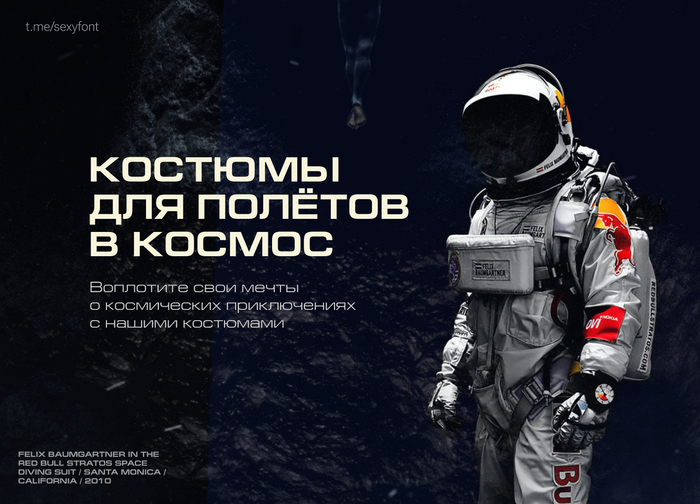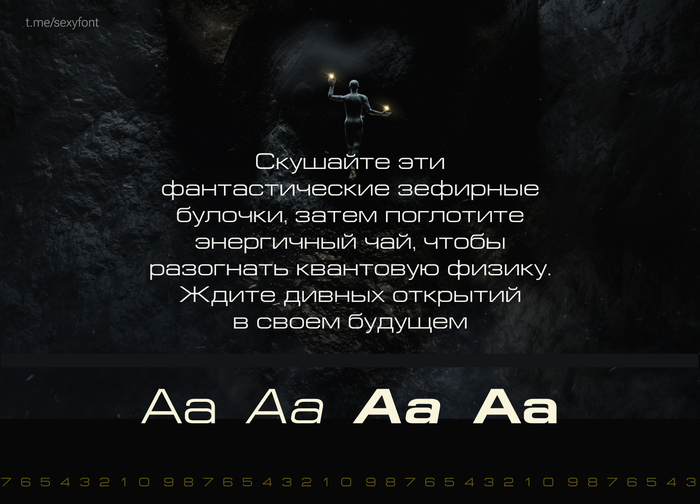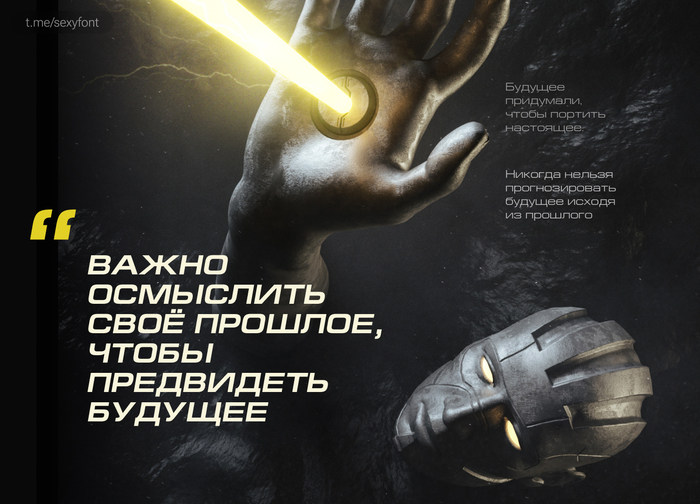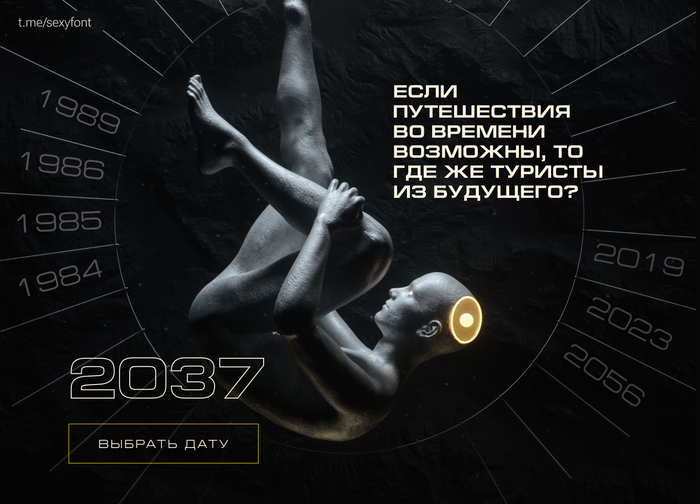
Шрифт EuropeExtendedC
Футуристичный кириллический шрифт. Этот шрифт старше многих читателей) разработан в фирме TypeMarket в 1992-1993 (дизайнер А.Кустов)